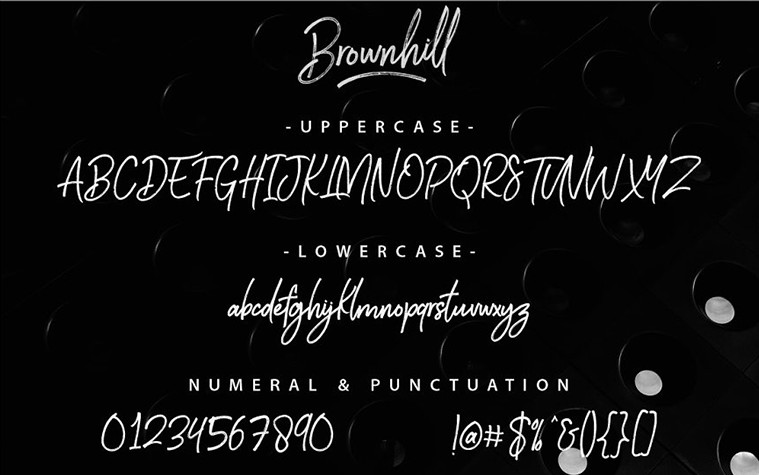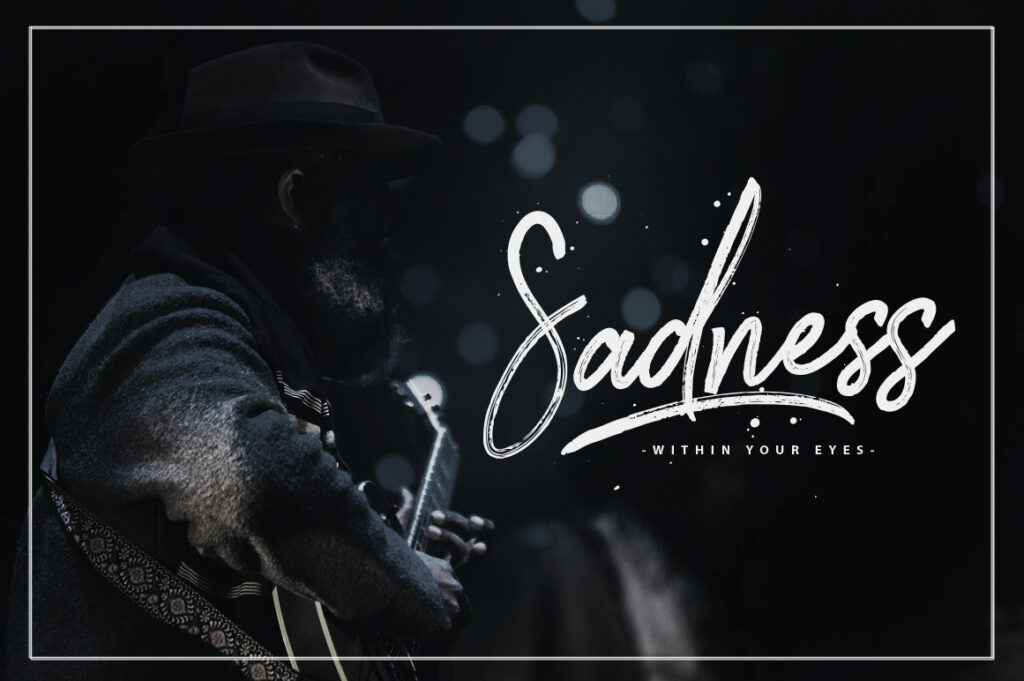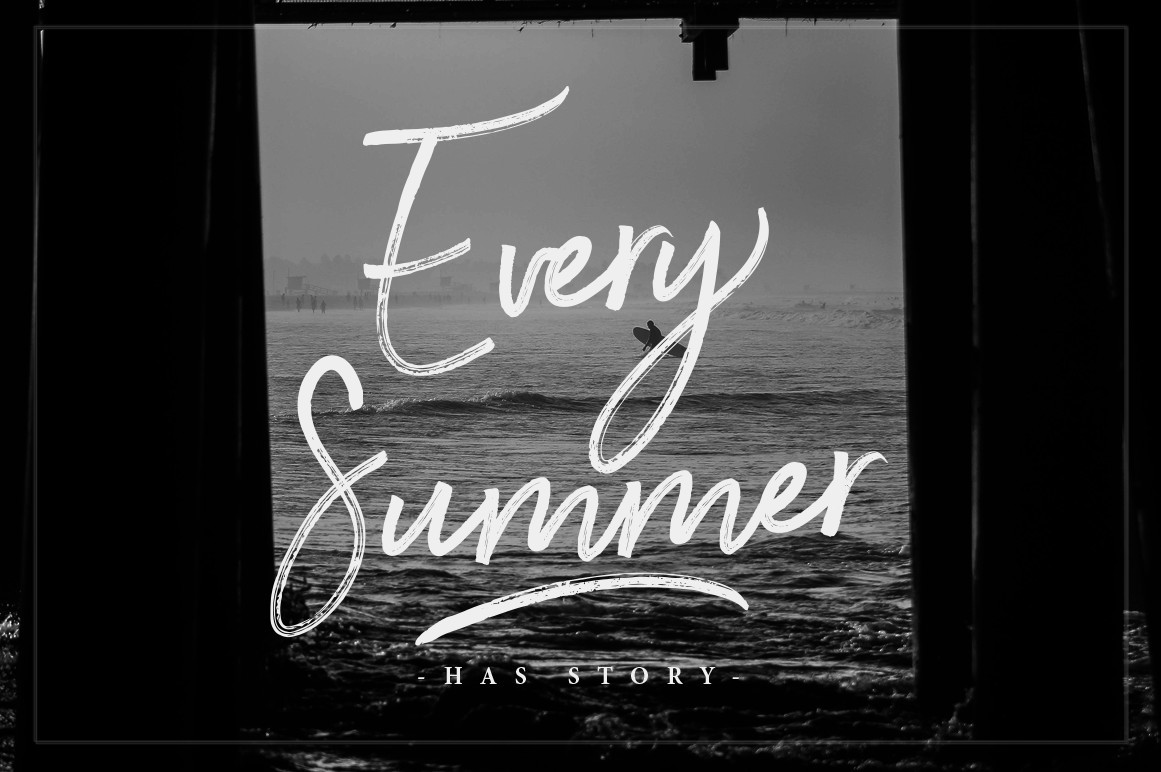
Font Svn Brownhill script là gì?
Font SVN Brownhill Script là một phông chữ dạng script (chữ viết tay) mang phong cách nhẹ nhàng, thanh lịch và vô cùng hiện đại. Đặc trưng của phông chữ này là các nét nối mềm mại, tự nhiên như được viết bằng bút mực cao cấp. Đây là lựa chọn hoàn hảo cho các thiết kế thiệp cưới, nhãn hàng mỹ phẩm, bao bì yến sào hoặc các dòng sản phẩm dành cho phái đẹp yêu cầu sự tinh tế cao.
Ưu điểm lớn của bộ phông này chính là khả năng tạo ra sự sang trọng cho các tiêu đề và logo. Tuy nhiên, nếu không sử dụng bản việt hóa chuẩn, các lỗi hiển thị dấu sẽ làm hỏng toàn bộ bố cục thiết kế. Bản download font SVN Brownhill Script việt hóa do In Viva cung cấp đã được căn chỉnh kerning và dấu thanh hoàn hảo, giúp bạn tự tin ứng dụng vào các dự án in ấn thương mại chuyên nghiệp.
Ứng dụng font SVN Brownhill Script trong thiết kế bao bì
Sự bay bổng của bộ chữ này mang lại vẻ ngoài cao cấp cho mọi ấn phẩm truyền thông của doanh nghiệp:
- Thiết kế logo và nắp hộp cứng: Tên thương hiệu dùng font Brownhill Script ép kim nhũ vàng trên nền hộp nhung tạo hiệu ứng vô cùng đẳng cấp cho các set hộp đựng trang sức.
- Sản xuất túi giấy thời trang: Font chữ này giúp túi xách đựng quần áo, phụ kiện trở nên “có gu” và thu hút phái nữ hơn, tăng khả năng nhận diện thương hiệu.
- In ấn sản phẩm gốm sứ: Hình ảnh chữ viết tay nghệ thuật in nung trên bộ ấm chén gốm sứ Bát Tràng là món quà tri ân khách hàng vô cùng tinh tế và bền bỉ.
- Thiết kế thiệp tri ân và Voucher: Sử dụng Brownhill Script cho các dòng chữ như “Thank you” hay “Gift for you” giúp khách hàng cảm nhận được sự chân thành của doanh nghiệp.